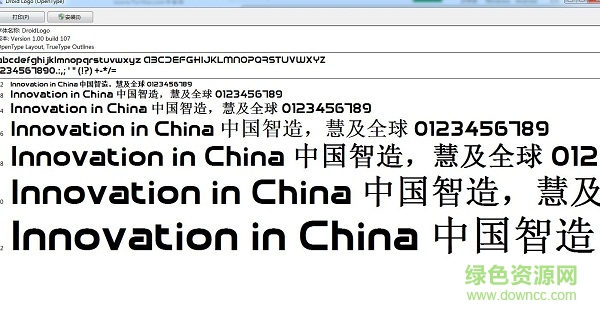
droidlogo
droidlogo字體是一款結(jié)構(gòu)獨(dú)出心裁的英文廣告字體,造型特異,充滿現(xiàn)代感,適合用在logo設(shè)計(jì)、廣告制作或是繪制墻報(bào)等方面,非常醒目,有需要者歡迎在綠色資源網(wǎng)免費(fèi)下載!
現(xiàn)代字體特征
現(xiàn)代字體設(shè)計(jì)趨于清晰簡潔,為迎合現(xiàn)代特征,字體設(shè)計(jì)被簡化,襯線逐漸被去除,線條也不再有粗細(xì)之分,干凈利落,更具機(jī)械繪制的特點(diǎn)。
droidlogo
個(gè)性字體的設(shè)計(jì)
根據(jù)廣告主題的要求,極力突出文字設(shè)計(jì)的個(gè)性色彩,創(chuàng)造與眾不同的獨(dú)具特色的字體,給人以別開生面的視覺感受,將有利于企業(yè)和產(chǎn)品良好形象的建立。